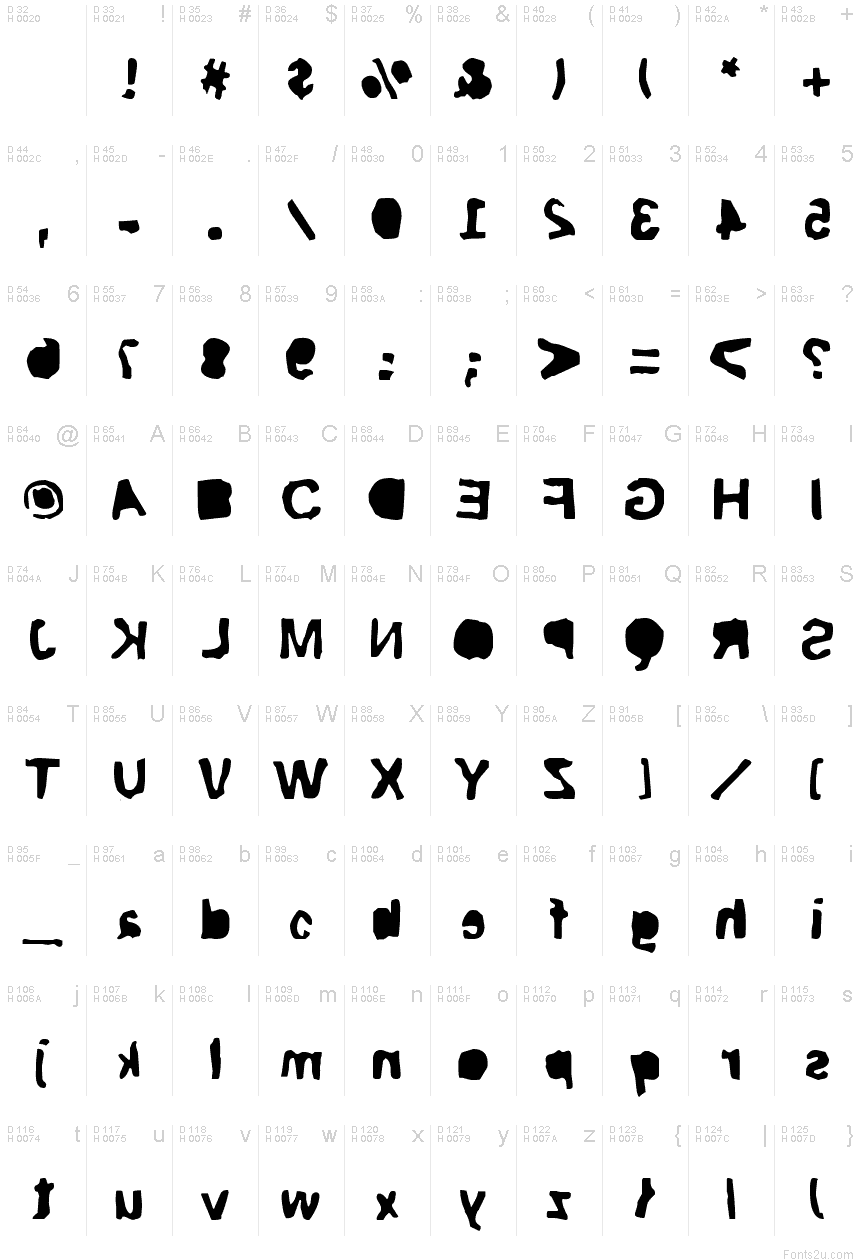
Rip TRASH Round von Manuel Viergutz ist eine kostenlose Cartoon-Display-Schrift aus klobigen, unregelmäßigen Buchstabenformen. Ihre weichen Ecken und schiefen Umrisse lassen den Schriftzug so wirken, als wäre er von Hand aus schwerem Papier ausgeschnitten. Die Formen sind stumpf und schwer.
Designer, die im Bereich Jugendunterhaltung oder schräger Comedy arbeiten, können den rauen Humor für Spielegrafiken und animierte Titelkarten nutzen. Die unregelmäßigen Silhouetten passen zudem zu Snack-Verpackungen, wo die Buchstaben Teil einer verspielten, maskottchenbasierten Identität werden können. Plakate für Kinderveranstaltungen und lose Merchandising-Artikel wie T-Shirts und gedruckte Aufkleberbögen passen ebenfalls gut zu den abgerundeten Formen und der bewusst tollpatschigen Konstruktion.
"rip TRASH" — Headline-/Display-Schrift mit sechs Stilen und 100 Glyphen einschließlich Akzenten.
- Stile: regular, mirror, cut, cutMIRROR, round, roundMIRROR
- Glyphen: 100 Glyphen einschließlich akzentuierter Zeichen